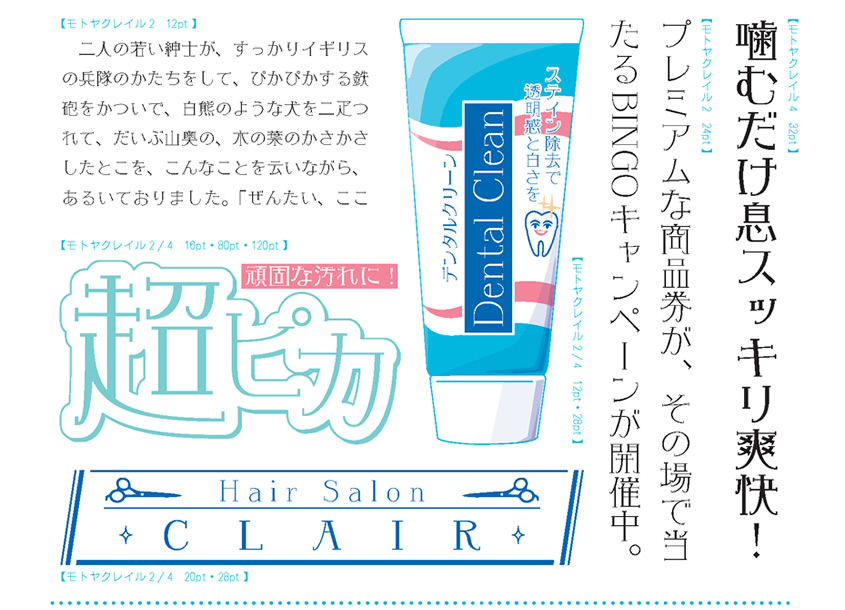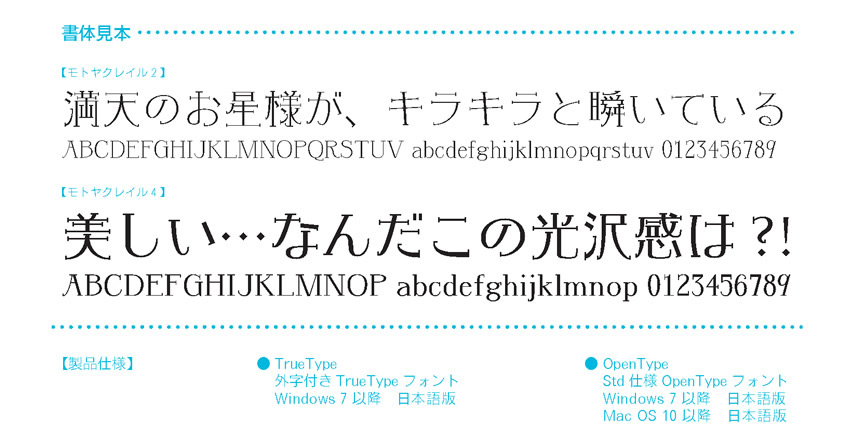
清潔感・高級感のあるデザイン書体「モトヤクレイル」に新たにウェイト(W4)が追加
~清掃・歯科衛生用品のパッケージや美容室の看板などに最適~
これまでのモトヤにないエレガントな表情を持つデザイン書体「モトヤクレイル」のご紹介。
この度このシリーズにウェイト4が追加になりました。
| ◆モトヤクレイルのコンセプトモトヤクレイルは、文章に「ツヤ」「光沢感」が付与されたデザイン書体です。 |  |
◆書体組見本・使用例
モトヤクレイルは、文字の表情として「清潔感」「高級感」を持ち合わせているため、
例えば清掃用品・歯科衛生用品・洗車グッズのパッケージやロゴ、美容室・サロンの看板屋キャッチコピーへの使用にも最適です。